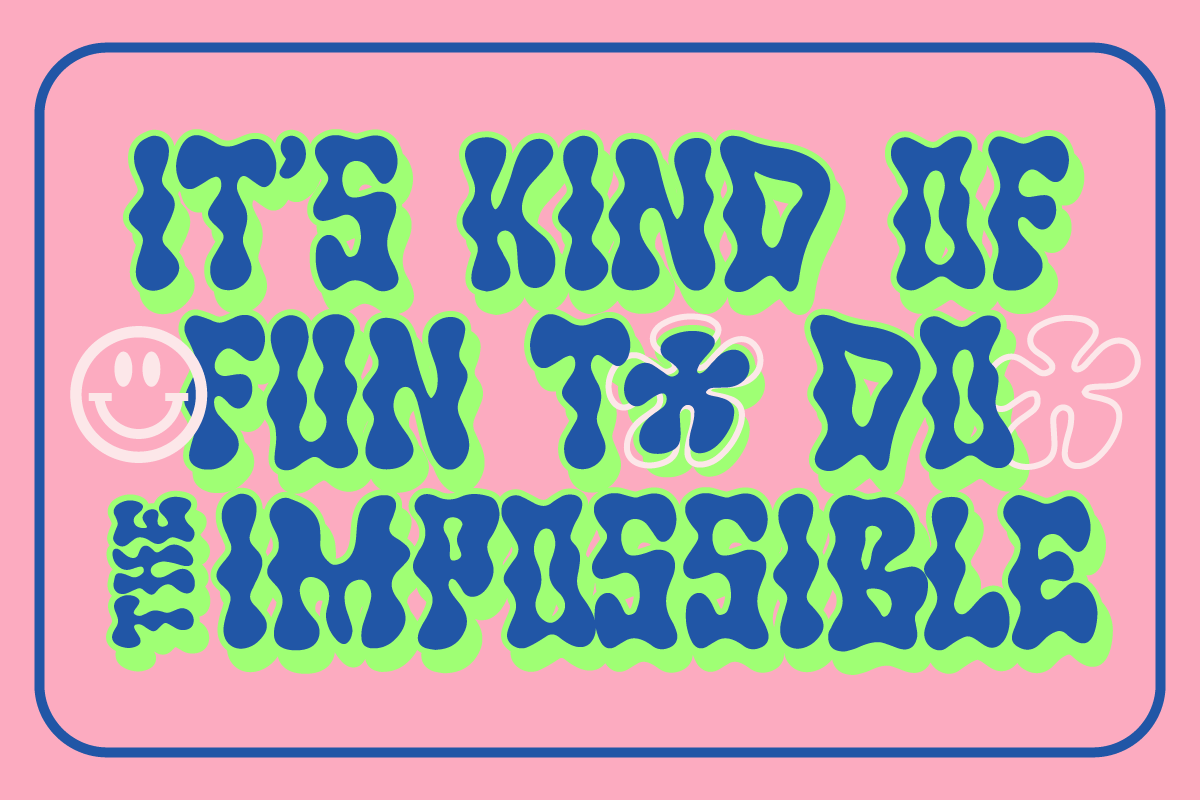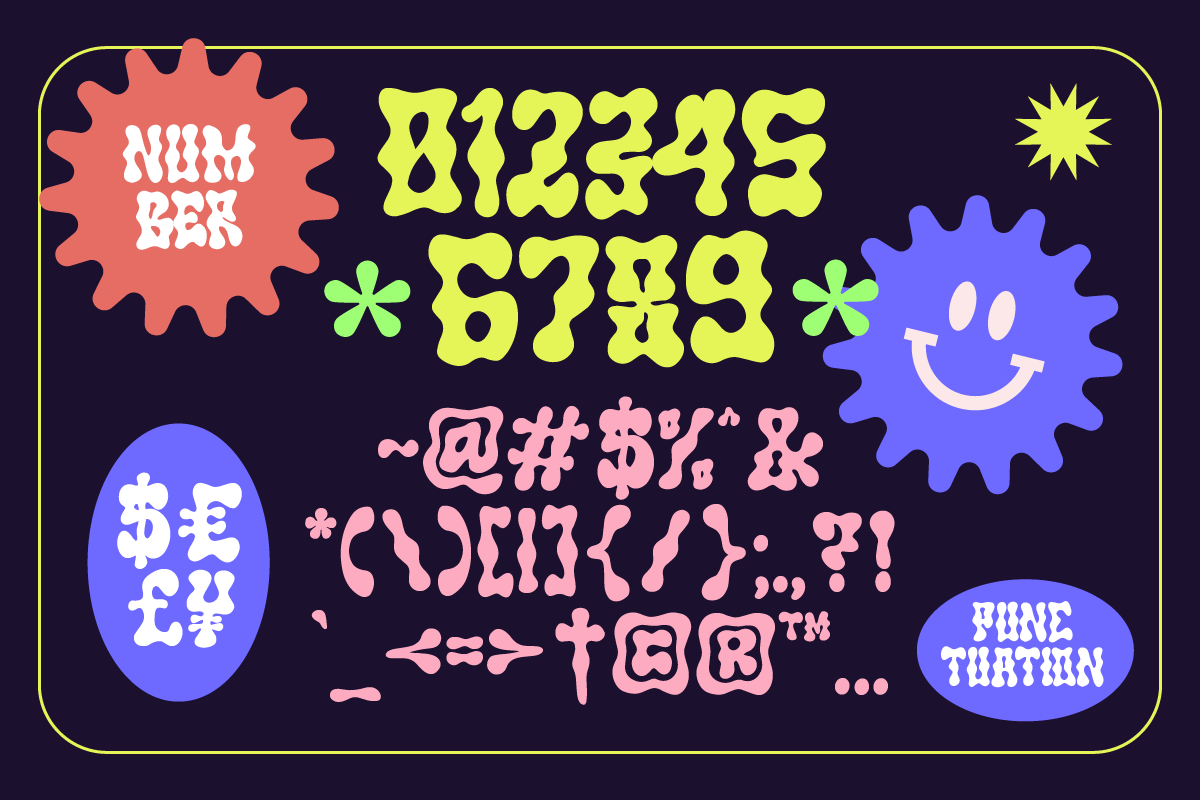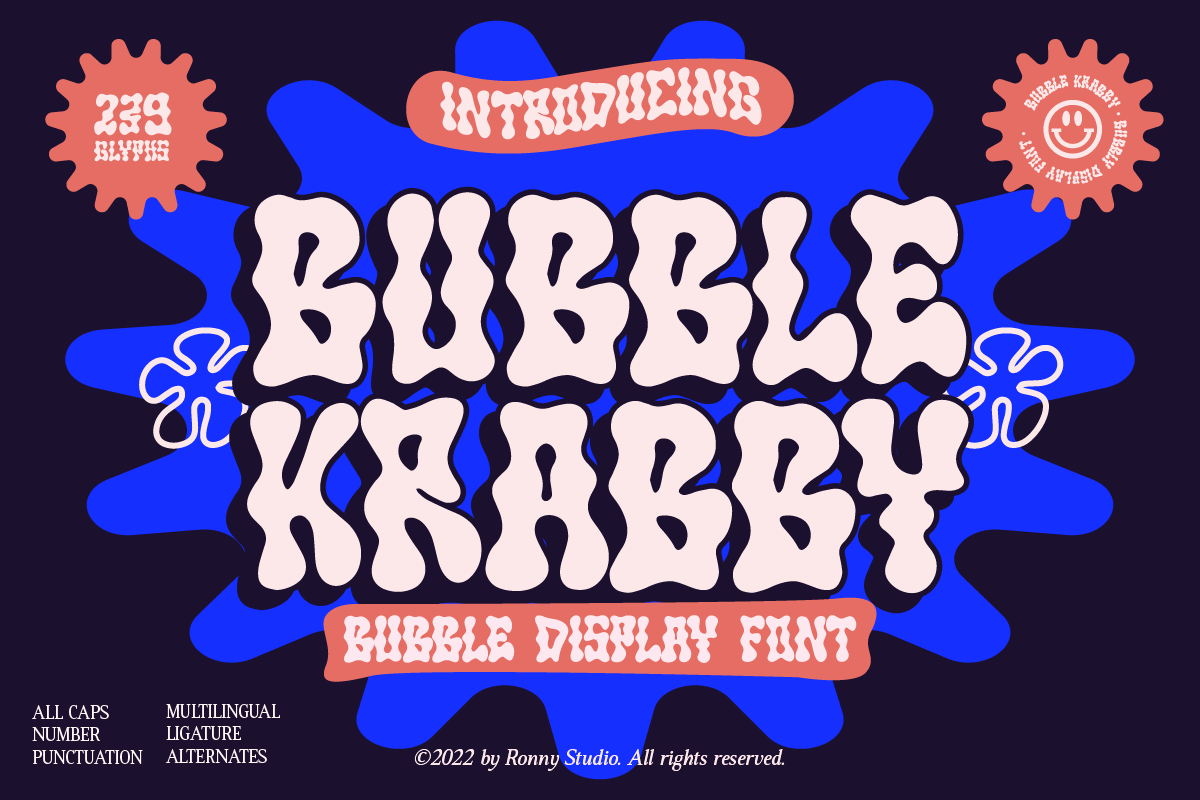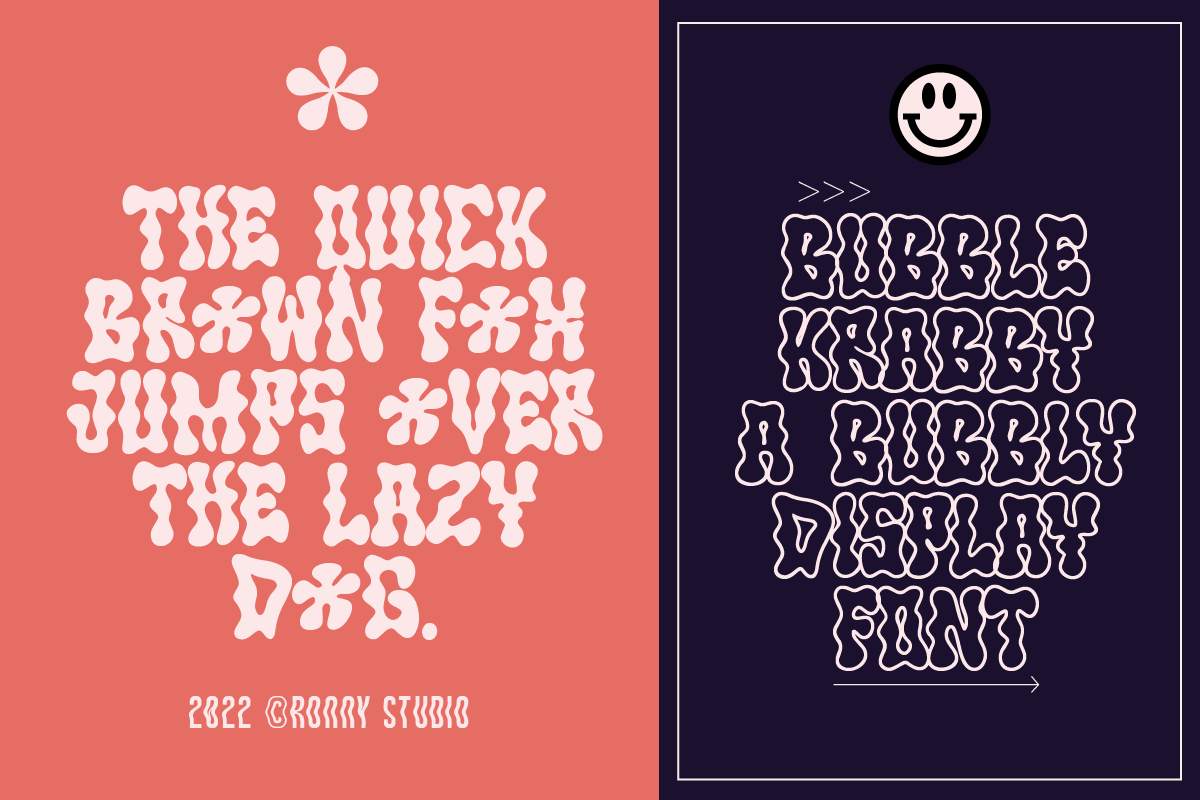
Bubble Krabby - Bubble Display Font
Bubble Krabby itu retro, berani, dan ceria, benar-benar menyatukan karya Anda untuk memberikan kesan retro. Ini adalah font yang sempurna untuk desainer yang ingin menambahkan sentuhan grafis psychedelic acid kontemporer yang dibuat dengan tangan ke dalam proyek mereka. Baik itu poster, majalah, Instagram, daring, Game, atau branding.
• Huruf Besar & Huruf Kecil
• Angka & Tanda Baca
• Ligatur & Alternatif
• Dukungan Multibahasa